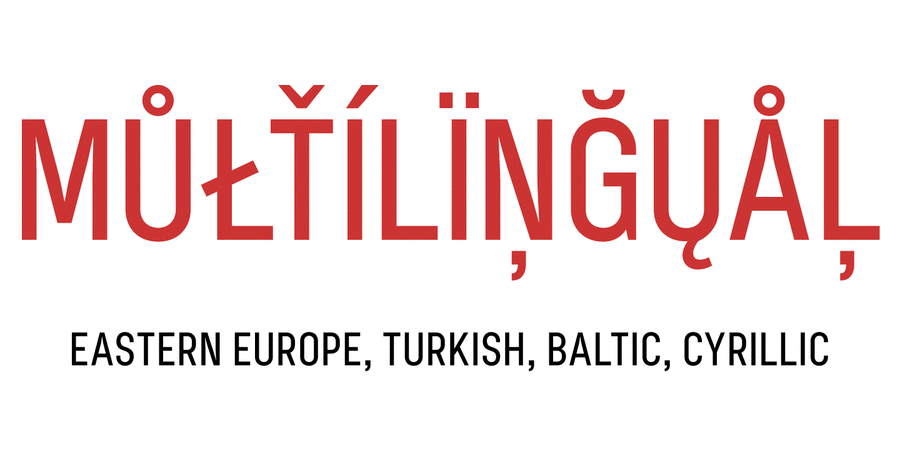
Геометричний ґротеск у шести накресленнях від тонкого до жирного, відмінно підходить для заголовків, реклами, плакатів. Шрифт розробив Сергій Ткаченко у 2012-2014 роках.
Асоціації з сімейством шрифтів Bond 4FОсобистість і характер гарнітури:
точний, рівний, прямокутний, стабільний, стійкий, техногенний, стрункий, статичний, міський, скляний, гострий, крихкий, дротяний, розумний, худий, Простий, урбаністичний, переконливий, твердий, серйозний, надійний, впевнений, сильний, індустріальний, авторитетний, автоматичний, сталевий, міцний, формальний, діловий, сучасний, монотонний, логічний, прагматичний, практичний, штучний, холодний, машинний, інженерний, мотивуючий, крутий, залізничний, креслярський, робочий, залізний, амбітний, архітектурний, відповідальний, важливий, військовий, важкий
техніка, прилад, архітектура, наука, дизайн, Місто, технології, верстат, інструмент, урбаністика, рентген, завод, інженер, автоматика, інститут, космос, новини, промисловість, електростанція, енергетика, хмарочос, машинобудування, порт, конструктор, авіація, літак, будівництво, вагон, креслення, залізниця, робочий, астрономія, ремонт, армія, зброя, архітектор, Футбол, спорт, дорога, кінотеатр, цигарки, тренажери, ракета, супутник, страйкбол, селфі, вантажівка, далекобійник, мотор, двигун Гарнітура має ознаки стилів: